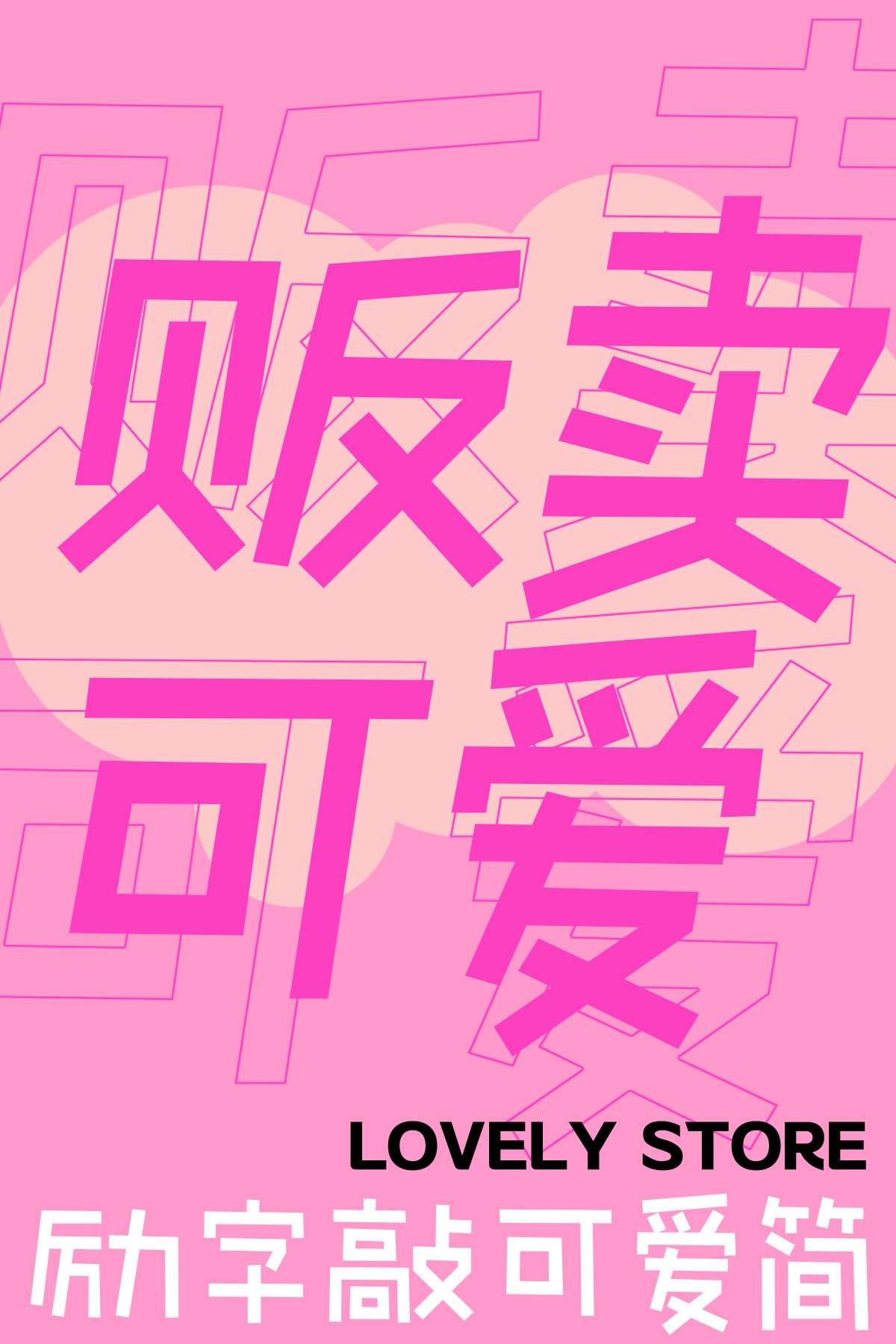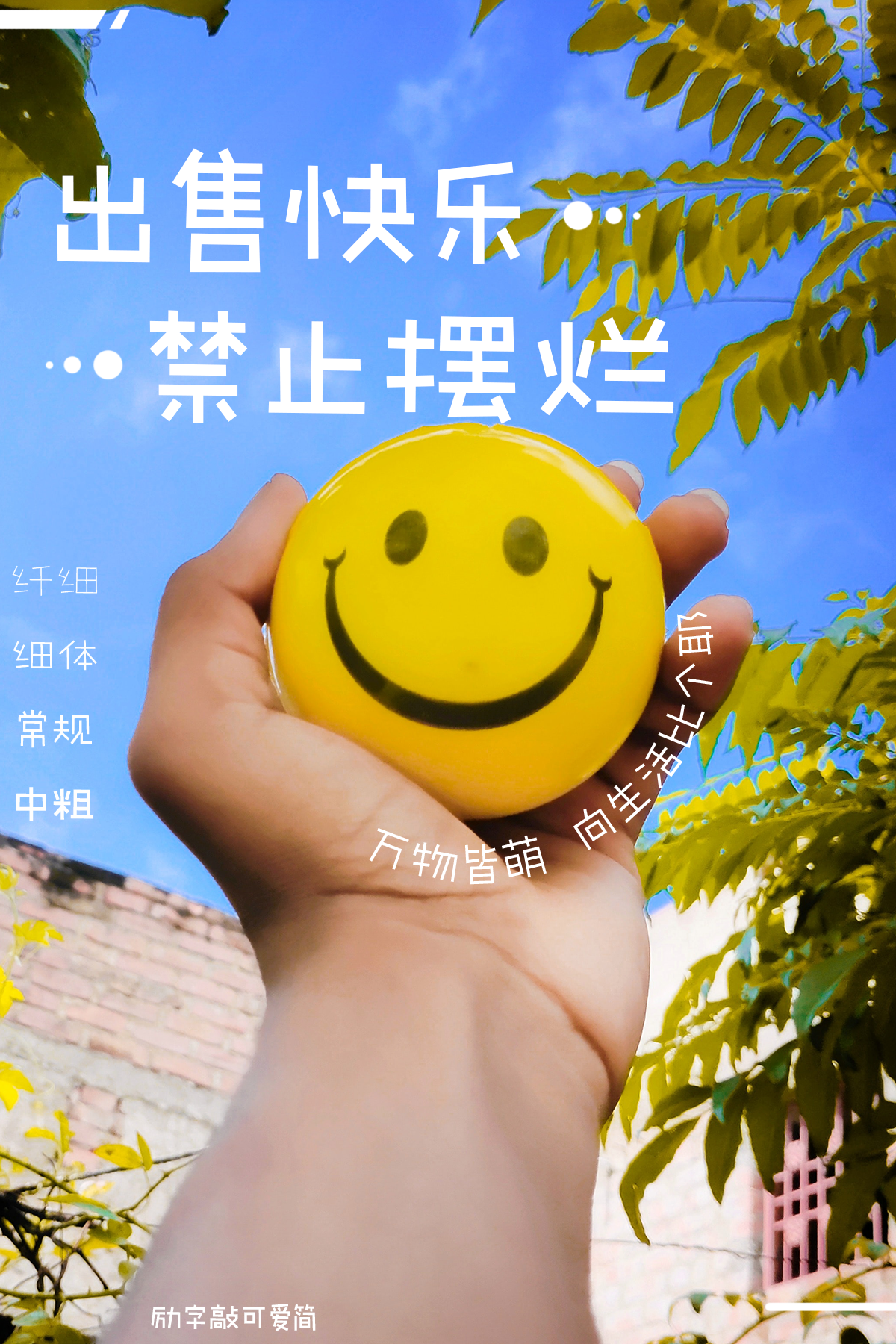
励字敲可爱简 常规
Dream-CuteGB
字体名称:
励字敲可爱简 常规
字符集:
GB2312-1980
字体语言:
简体
书体类型:
黑体
字体类型:
普通字体
字体字重:
常规(Regular)
一款略带俏皮,充满趣味与想象的创意直线字。手写的圆润线条在保留辨识度的前提下,省略部分笔画,简单,明快的线条,独特的形式,营造用心书写的随性,让字体更具手绘感,带来手写的柔软和温暖。